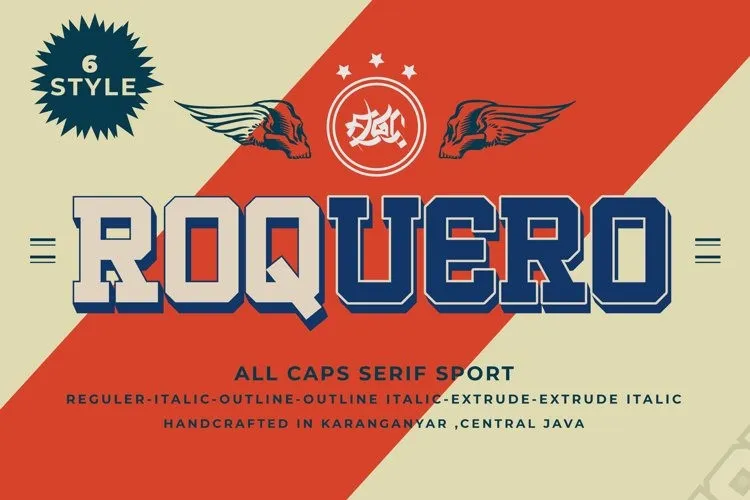
A fonte “Roquero Font” é uma escolha incrível para qualquer projeto que busque destaque visual e elegância. Ela foi criada por FallenGraphic Std, incorporando elementos de linhas grossas com temas de insígnias. Este design slab serif se destaca como um recurso perfeito para trabalhos de marcação, frases inspiradoras ou ilustrações em geral. Perfeita para uma variedade de aplicações gráficas, “Roquero Font” é uma fonte display que irá tornar qualquer projeto mais poderoso e atraente. Suas linhas robustas criam um tom elegante e moderno, garantindo que sua mensagem seja notada com clareza e força. Este design é ideal para aqueles buscando uma fonte de alta qualidade para projetos de marca ou criação de conteúdo.